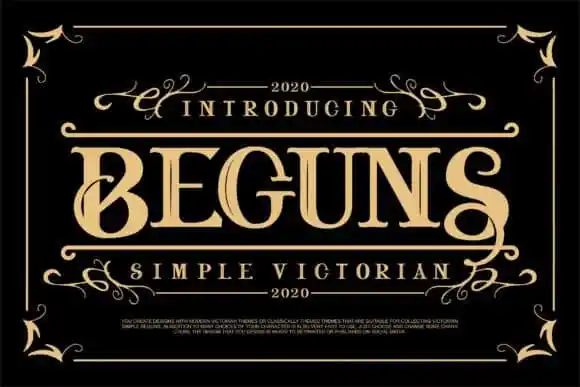
Beguns Display Font – Fonte Grátis
Beguns Display Font
A “Beguns Display Font” é uma tipografia moderna em sans serif com um sentido fresco de letras maiúsculas. Desenhada por Vunira e disponibilizada no 99designs, esta fonte apresenta uma estética elegante e arrojada que se adapta perfeitamente para ambientes gráficos criativos. Suas letras em maiúsculo com ligaduras oferecem flexibilidade quando se trata de criação, permitindo aplicar essa fonte em diversos tipos de mídia, incluindo títulos, logotipos, cartazes, embalagens e até mesmo estampas de camisetas. Ideal para quem busca uma fonte que possa transformar suas ideias criativas em algo realmente especial, a “Beguns Display Font” pode ser sua escolha perfeita para dar vida à sua próxima produção visual.